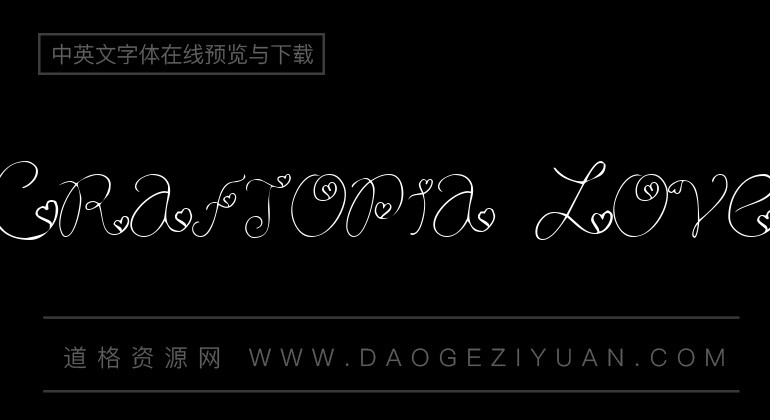
Craftopia Love 字体是一款精美的脚本字体,由 Craftopia 团队开发。它的特点是柔和的笔画,拥有精美的细节,易于阅读,可以用于创作或设计工作。它可以用于商业或个人用途,也可以用于印刷品,网页,平面设计,标志等。它拥有多种字重,可以满足您的各种需求。内容介绍
Craftopia Love是一款非常不错的手写艺术字体,具有很好的视觉感,适合于文化类的宣传设计、商业类品牌的广告和产品包装设计以及个性化文字排版等较多场景。